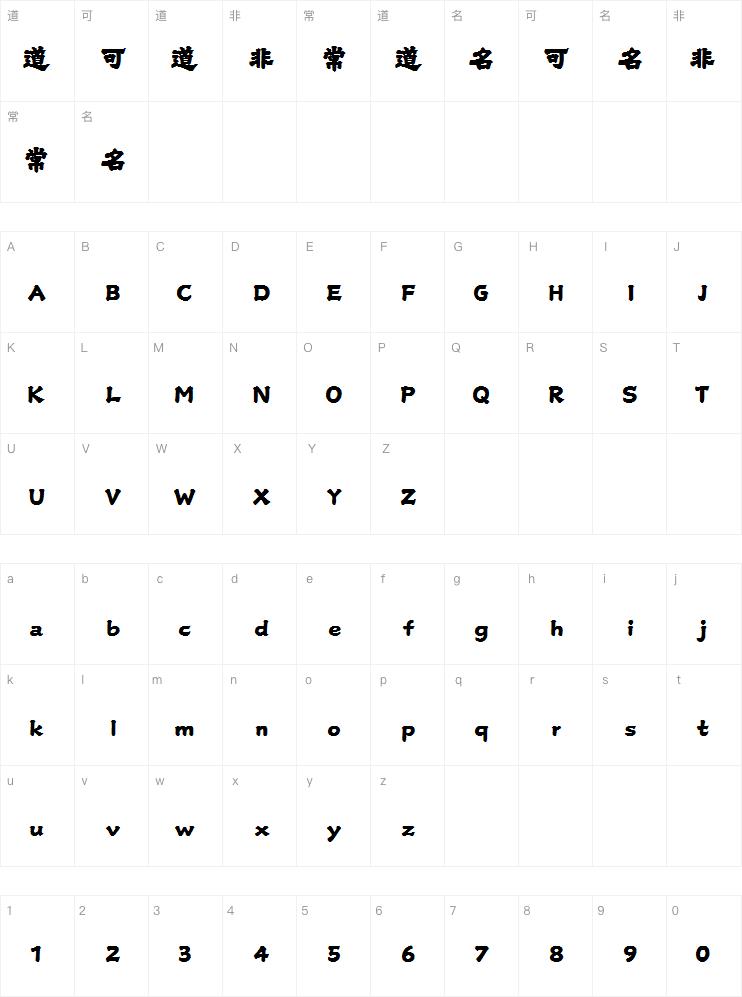
山海风华隶,是一款全新的字体,包含汉字9169个,符号200+个,是一款带有隶书韵味的国潮风字体。该字体气吞山河,雄健有力。整体以隶书为骨,字形扁方,取正势,重心平稳,结体紧实,笔画铿锵有力,横平竖直,书写的顿笔风格强烈。古朴浑厚,笔画与字形间透露着隶书的古雅和刚劲的特点,在浑厚的同时而又极富张力,桀骜不驯的特性,风华并茂。它的笔画充满力量感,组合搭配极富强烈的节奏感。在粗细的纵横间,拥有非常规的张力特性。从而使得该字体字形在浑厚的同时而又极富张力。它的笔画充满力量感的同时,又蕴含着朴拙感。在粗细的纵横间,拥有非常规的张力特性。笔画的楷书运笔笔势效果使字体的气息更加流畅,笔画间的关系密不可分,同时也增加了字体的自由洒脱之感。这款字体古韵悠扬而不失灵动,静中有动,收放有序,适合作为标题字体应用于书籍封面、影视标题、展览广告等多种场景。